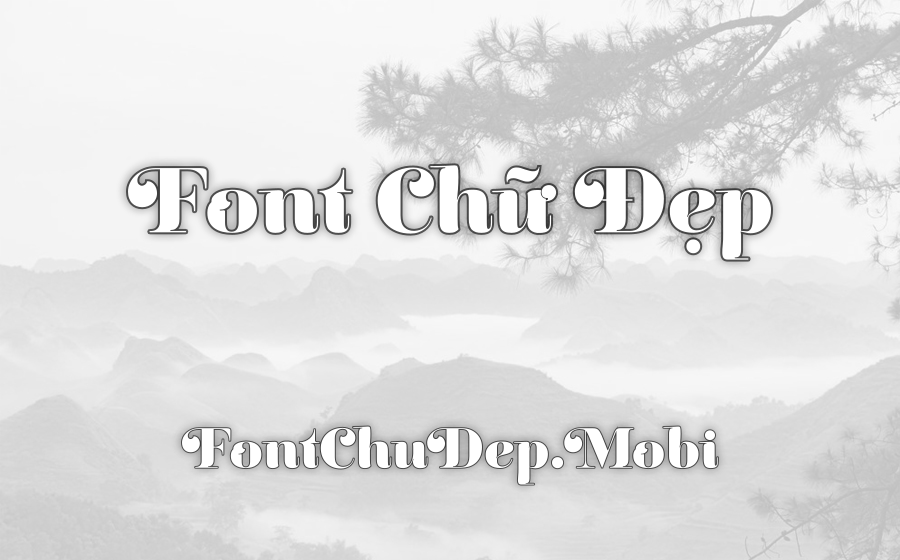
Font UVF Reina 12 Pro Việt Hóa
UVF Reina 12 Pro
Trải nghiệm Reina 12 Pro thật sự là một chuyến phiêu lưu trong thế giới của kiểu chữ serif trang trí. Được chắp bút bởi nhà thiết kế Maximiliano R. Sproviero, font này có một sức hút đặc biệt nhờ vào sự kết hợp giữa đường nét đậm và những nét mỏng được nhấn nhá đầy tinh tế. Sự tương phản này không chỉ tạo ra vẻ đẹp sang trọng mà còn mang lại nét thanh lịch thực sự ấn tượng.
Một điều thú vị là Reina 12 Pro mặc dù mang theo hơi thở cổ điển nhưng lại không hề thiếu đi nét hiện đại. Đây chính là yếu tố giúp nó trở nên lý tưởng cho các dự án cần sự nổi bật và cuốn hút. Được Việt hóa hoàn toàn, font chữ này hỗ trợ đầy đủ các ký tự tiếng Việt, mở ra một thế giới khả năng vô biên cho người dùng tại Việt Nam khi ứng dụng trong các thiết kế của họ.
Sự linh hoạt của Reina 12 Pro thể hiện rõ nét khi bạn sử dụng nó cho các mục đích như thiết kế logo, tiêu đề hay thậm chí là thiệp mời và các ấn phẩm nghệ thuật. Nó tỏa sáng rực rỡ trong bối cảnh của các sự kiện quan trọng như lễ hội, lễ cưới hay những dịp văn hóa đặc biệt. Không dừng lại ở đó, font chữ này còn là người bạn đồng hành tuyệt vời trong các ngành nghề sáng tạo như thiết kế đồ họa, nghệ thuật trang trí hay xuất bản.